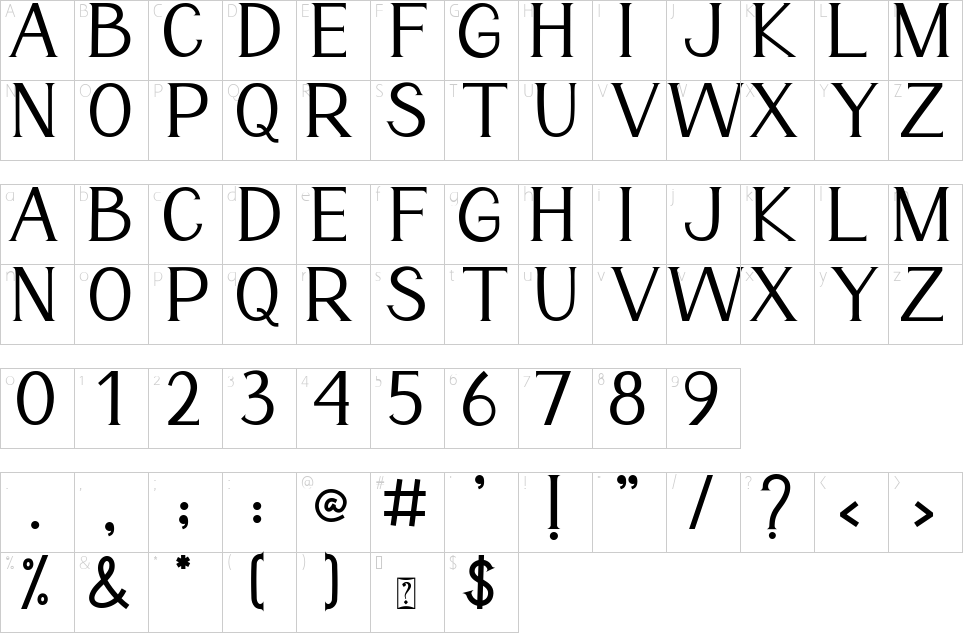
A Monaline é uma fonte elegante e atraente que oferece um charme sofisticado a qualquer projeto. Desenvolvida pela AEN Creative Studio, esta fonte vem para aqueles que valorizam uma apresentação limpa e minimalista. Com seu design cuidadosamente elaborado, a Monaline é perfeita para aplicações que exigem um certo tom de elegância, seja em websites, editoriais ou até mesmo em design gráfico. Com um total de 1,768 downloads, a Monaline está se tornando cada vez mais popular, oferecendo uma escolha versátil e impecável. Instale-a em seu próximo projeto e experimente um ar de sofisticação inegável.